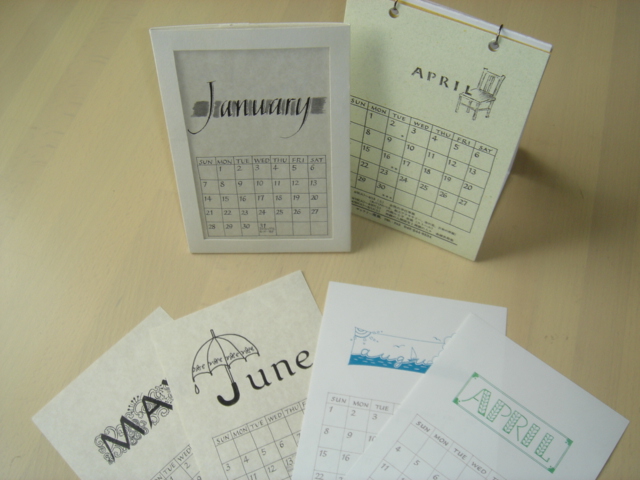
手作りカレンダー
1月から3月まではあっという間に過ぎてしまいますね。カレンダーをめくり忘れることもしばしば。
ふと思い出したのが手作りのカレンダー。もう5、6年前のことになりますが、クラスのみなさんと一緒に年末に卓上カレンダーを作っていました。3年くらいは続けたでしょうか。
一人1ヶ月、または2ヶ月と分担して、月の名前を好きな書体やデザインで書きます。それを12枚集めてコピーしていました。(なつかしの切り貼りコピー!)
カレンダーのスタイルはいつも下半分が曜日と数字(玉、というのだそうですね)で同じようなものですが、書き手が毎回違うのでバラエティーに富んだ12ヶ月のできあがり!
はがきサイズにカットした12枚を紙製のケースに入れたり、上をリングで止めたり・・・。
簡単なものでしたが、参加人数分だけ作ればいいのでラクチンな手作りでした。
一人でやるのは大変なことでも人が集まれば苦もなくできることってありますね。